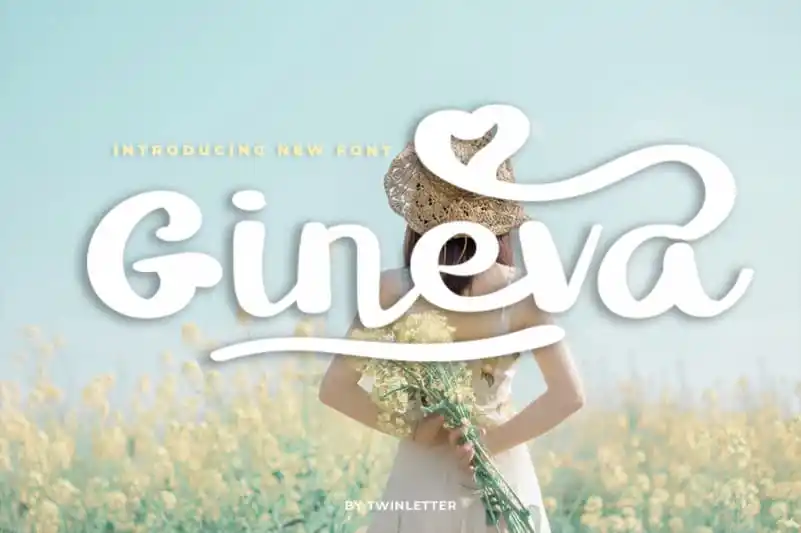
Gineva Script Font – Download Grátis
A Gineva Script Font é uma magnífica fonte escrita a mão cuidadosamente criada com um toque de elegância. Esta combinação de elegância eterna e autêntico alinhamento, oferece uma experiência única no mundo das fuentes. Com seu estilo clássico inigualável, ainda mantém uma sensação amigável e descontraída. É a fonte perfeita para criar designs originais e impressionantes. Sua elegância perpassa em toda palavra, desde os traços finos até os contornos mais amplos, transmitindo um senso de profissionalismo imparável que se sobressai sem perder o charme pessoal. Perfeito tanto para designers digitais quanto para artistas gráficos, a Gineva Script é uma escolha inteligente para qualquer projeto exigente em busca de uma fonte autêntica e memorável. A sua elegância e sofisticação são perfeitas para ilustrar mensagens que precisam ser memoráveis. Seja você um designer digital ou artista gráfico, a Gineva Script é uma fonte indispensável para qualquer projeto, seja ele grande ou pequeno.